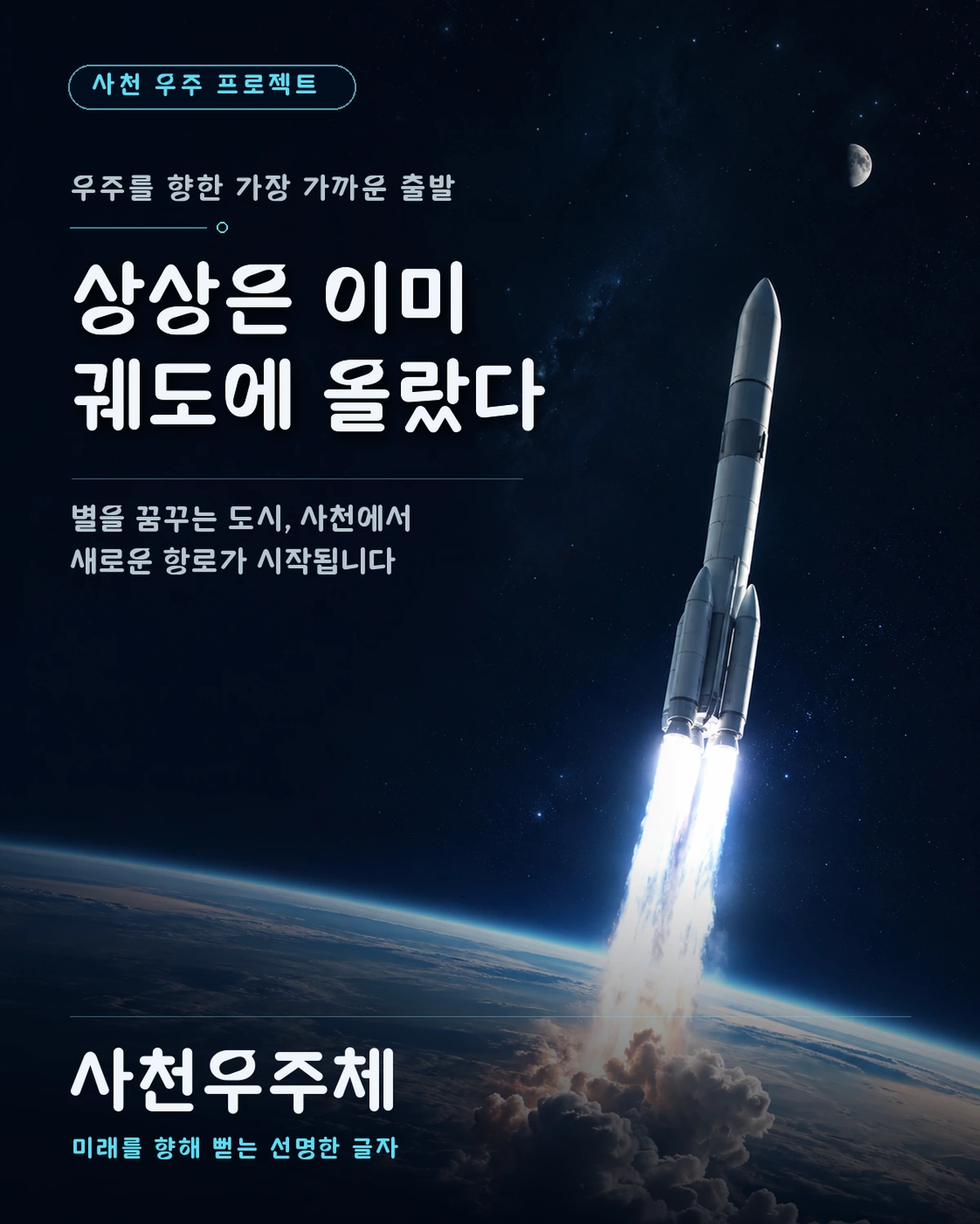
사천우주체 — 사천시에서 배포하는 무료 폰트입니다. 우주가 아니라 한글의 짜임에서 출발해, 우주항공 도시의 미래지향적 인상을 담아낸 디스플레이 서체
사천시가 2025년에 사천항공체와 함께 공개한 전용서체입니다. 만든 계기가 구체적입니다. **우주항공청 개청 1주년과 제1회 우주항공의 날을 기념**해, 대한민국 우주항공수도 사천의 품격을 드높이고 차별화된 도시 이미지를 만들고자 개발했다는 것입니다. 우주항공청이 실제로 사천에 있고 2024년에 문을 열었습니다.
조형의 출발점이 뜻밖입니다. 우주가 아니라 한글입니다. **천과 지, 인을 기반으로 우주의 광활함과 신비함을 형상화**했다고 밝히고 있는데, 천지인은 훈민정음의 모음 창제 원리입니다. 한글을 만든 원리가 우주라는 관념을 거쳐 사천의 정체성으로 이어지는 3단 구조인 셈입니다. 여기에 중상단에 맞춘 글줄과 꽉 찬 모듈 형태를 더했다고 설명합니다.
파일에서 재어 보면 받침 유무에 따른 높이 차가 거의 없는 네모틀이고 낱자는 정사각형에 가까우며 자면을 넉넉히 채웁니다. 제작사 사양에는 한글 2,780자로 적혀 있지만 폰트픽이 서비스하는 파일은 현대 한글 11,172자를 모두 담고 있습니다.